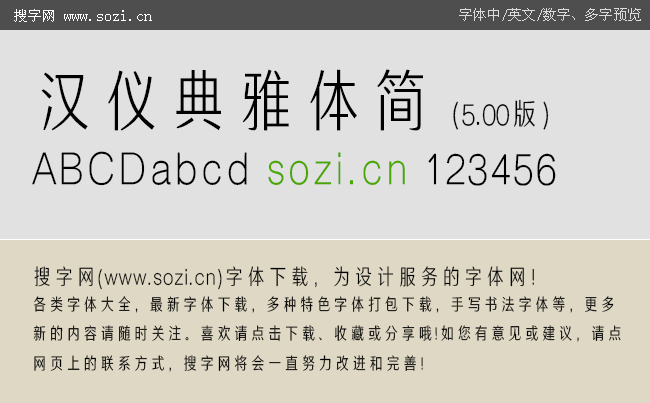
漢儀典雅體簡(jiǎn)(HYDianYaTiJ)
搜字網(wǎng)給大家提供一款漢儀典雅體簡(jiǎn)下載。典雅體與清雅體為一組家族字,在氣質(zhì)上具有相似的高挑特點(diǎn),尾部收緊令筆畫柔軟富有彈性,但典雅體相對(duì)清雅體筆畫較粗,有一定的厚重感,氣質(zhì)上也多一份沉穩(wěn)。適用于畫冊(cè)設(shè)計(jì)、包裝設(shè)計(jì)、排版、海報(bào)設(shè)計(jì)等廣告設(shè)計(jì)應(yīng)用。